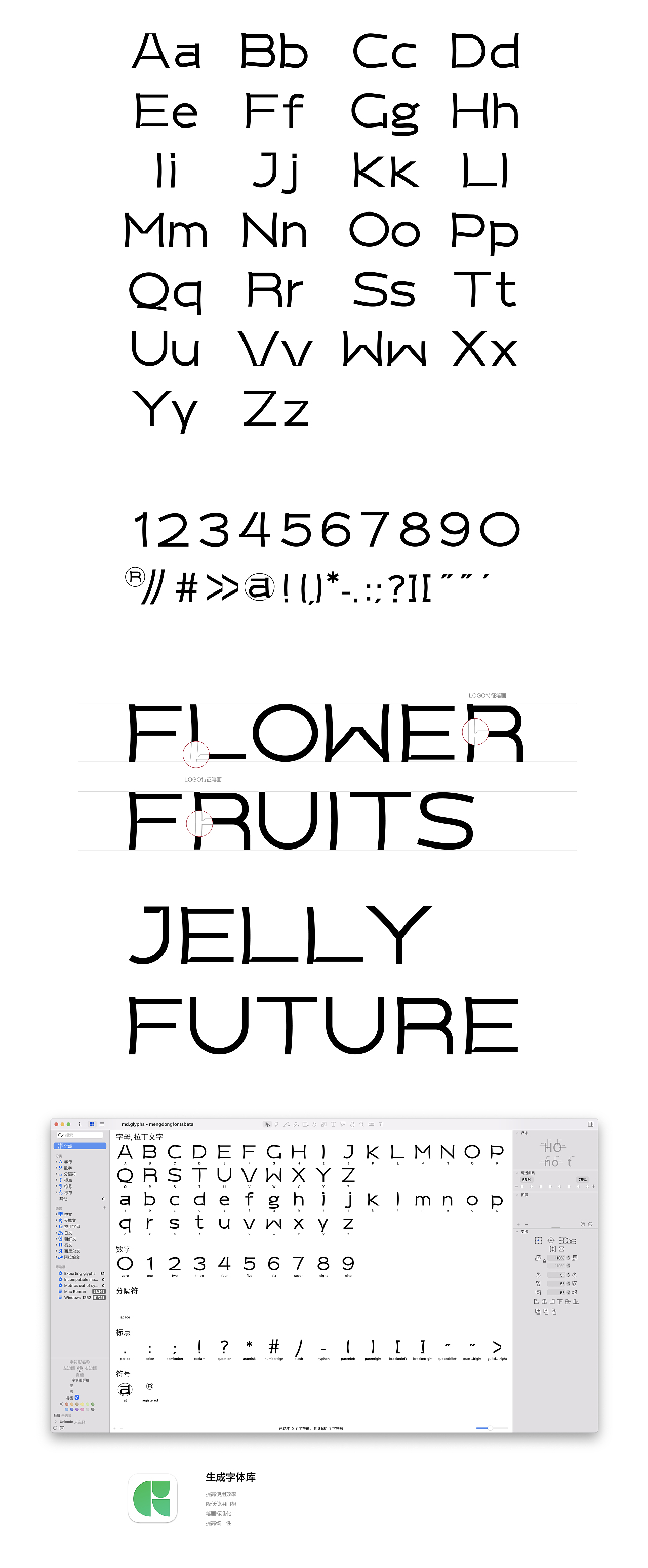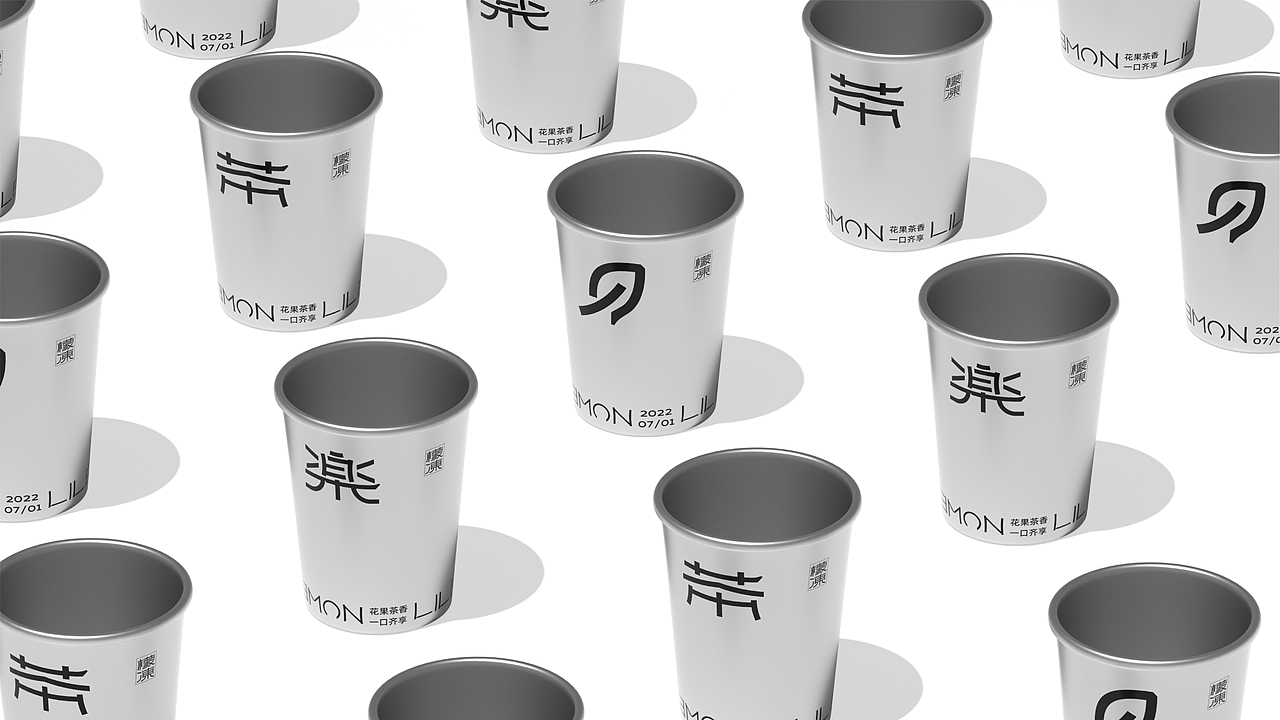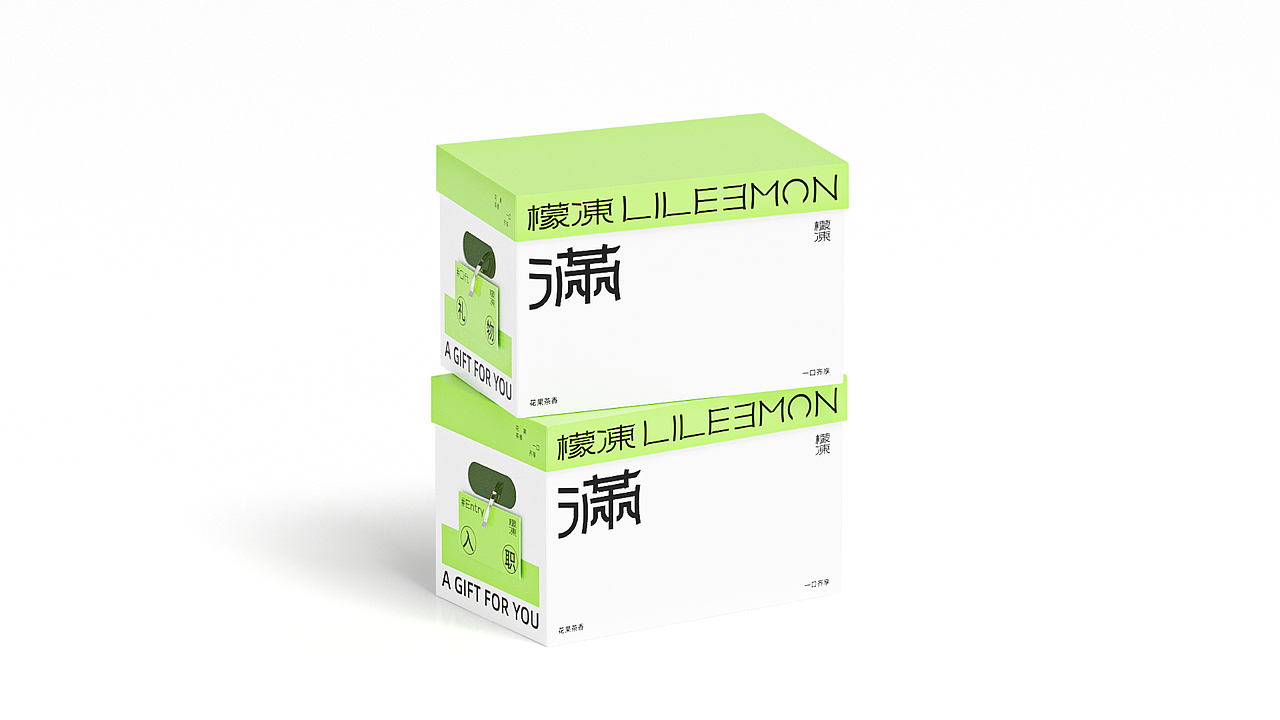
檬冻LILEEMON-品牌视觉设计-字体设计-VI应用设计
品牌:檬冻LILEEMON
品牌类型:快消/零食
檬冻是一家专研好吃高颜值、轻卡又健康的新式零食公司。以创新口味、优质食材、前沿工艺和新潮设计,革新童年记忆里的味道为核心概念。
此次为其设计整体视觉形象以logo,中英文字体进行延展设计,旨在以一种更全面的方式表达品牌健康,清晰,简约的核心气质。